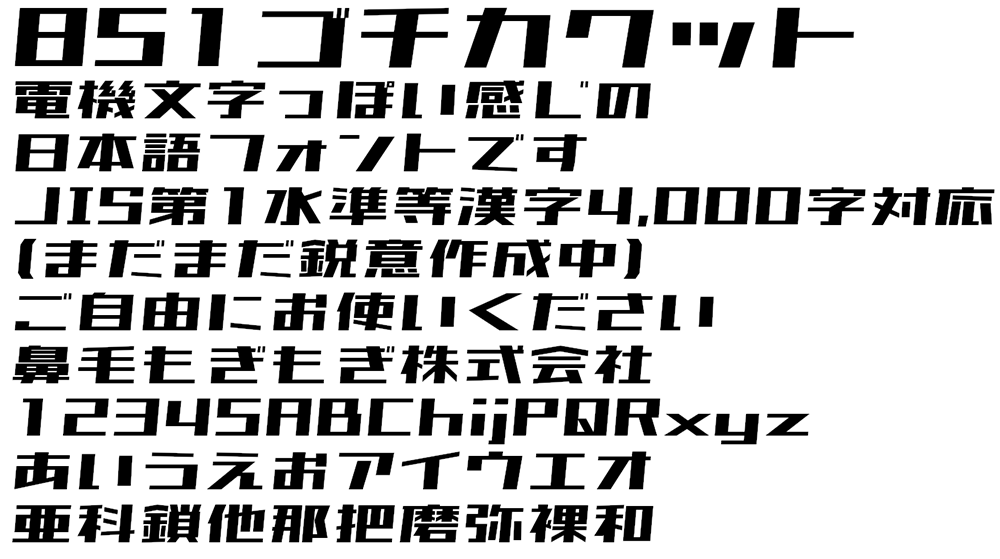
851电机文字体(851ゴチカクット)是由日本设计师 8:51:22 pm设计的一款充满锐利感的刚性日本字体,笔画和众多现代美术体相似,延续了横细竖粗的风格,竖画倾斜5°,看上去很有速度感,适合应用于海报、banner 的标题处,当前字符数:5146个字符(不包括空格)。
对应文字:平假名、片假名、拉丁文字(英语)、数字、希腊文字、基里尔文字、记号(某种程度)、汉字(包括常用汉字/人名用汉字在内的4437个文字)、其他情况下追加的文字
注意:这款字体适用于繁体和日文,不适用于简体中文,容易缺字。